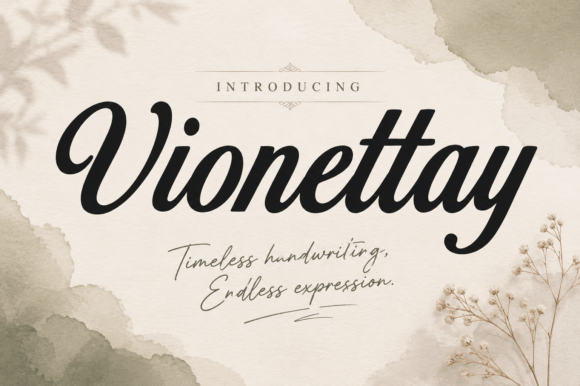
Vionettay
適切なデザイン要素を見つけるのは難しい場合がありますが、Vionettayは作品を即座に引き立てる優れたコレクションを提供します。
精密に作られたVionettayは、クリーンなベクター、滑らかなタイポグラフィ、そして安心のための商用ライセンスを提供します。
POD(オンデマンド印刷)製品、結婚式の招待状、またはソーシャルメディアのグラフィックを作成している場合でも、Vionettayは理想的です。